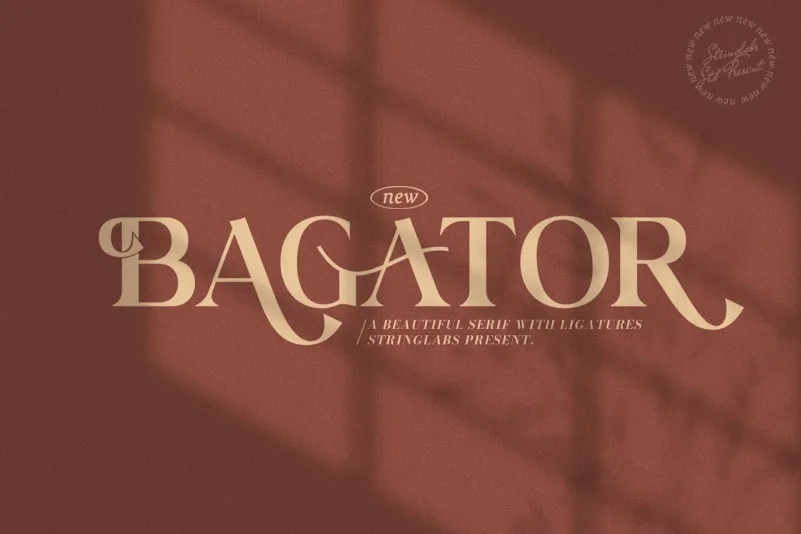
Bagator Serif Font – Fonte Grátis
Bagator Serif Font
A Bagator Serif Font é uma escolha perfeita para designers que buscam alegria e frescor no estilo serif tradicional. Este tipo-fonte foi criado pelo designer StringLabs, oferecendo um toque vintage, elegante e sofisticado sem deixar de ser moderno. Seus traços finos e leves dão ao texto uma aparência clássica e harmoniosa que se destaca em qualquer projeto. Com sua facilidade de combinação com uma ampla gama de projetos, a Bagator Serif é perfeita para designers buscam dar um toque único aos seus trabalhos. Combine-a com outros elementos gráficos modernos e notarás como ela complementa sem fazer nenhum tipo de competição. Perfect fit para sua próxima criação!